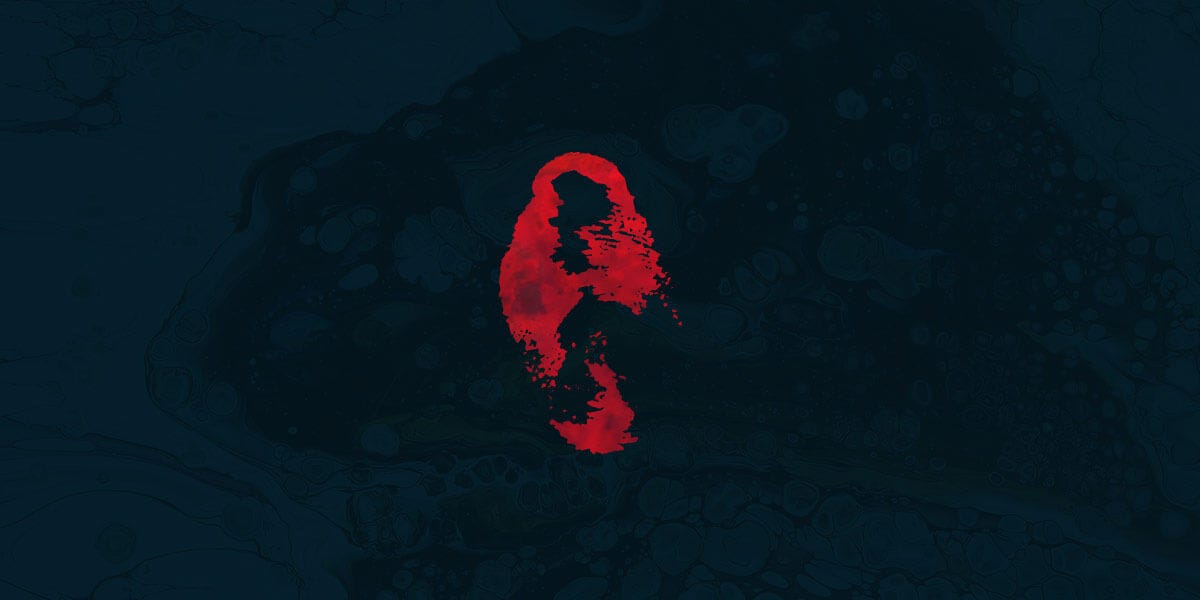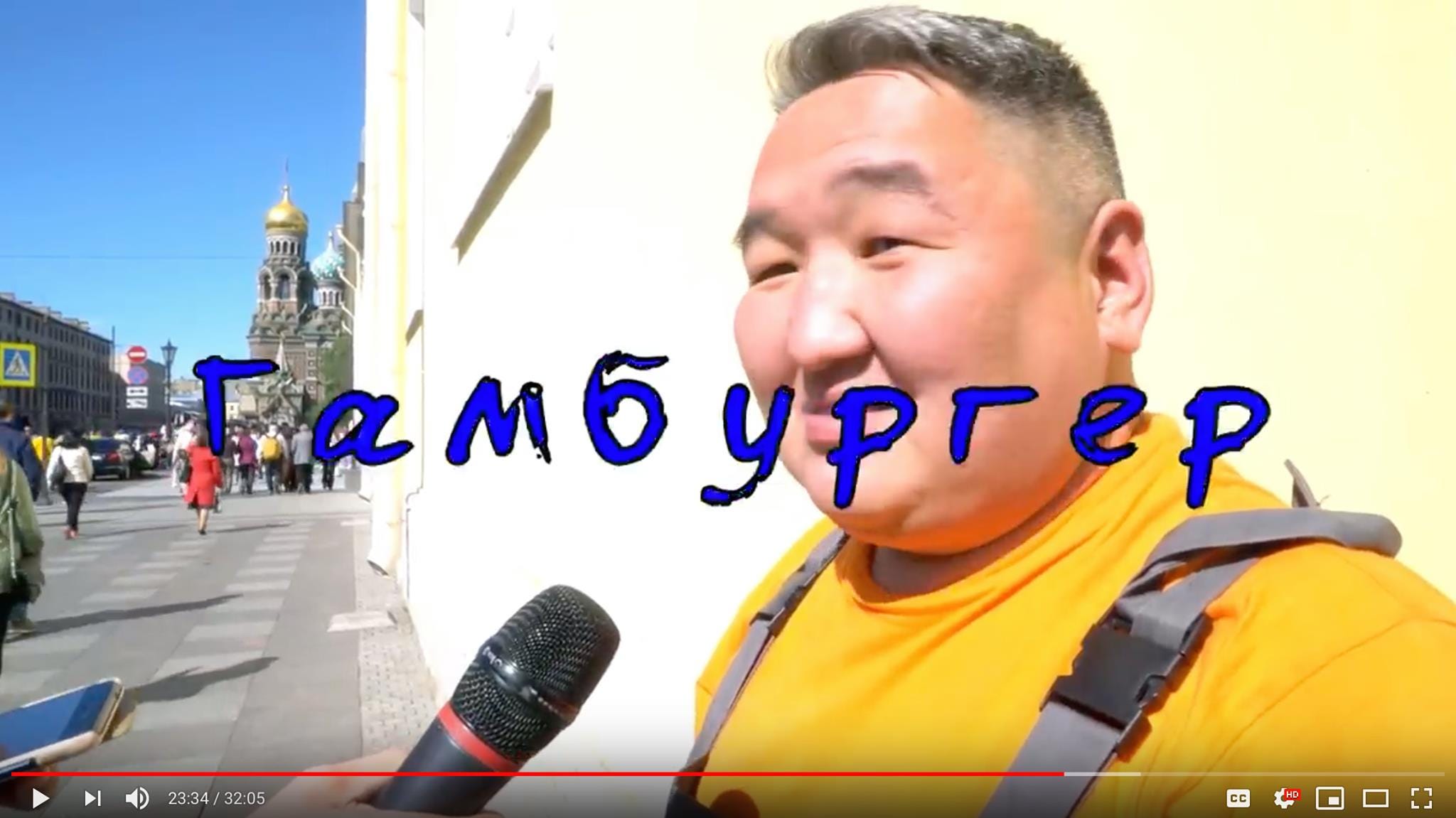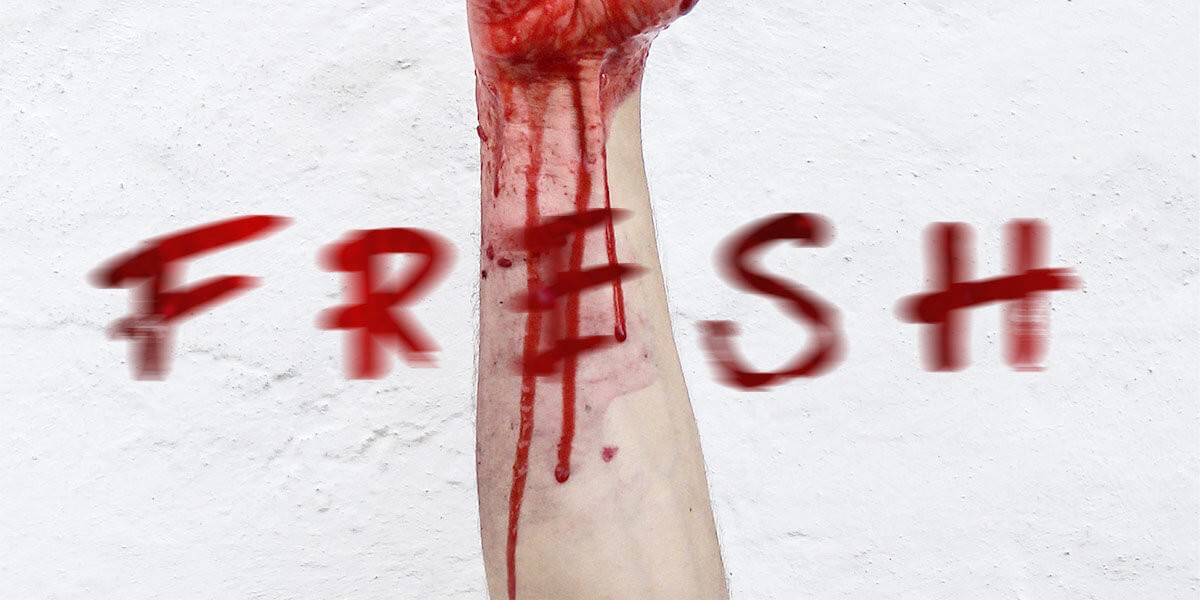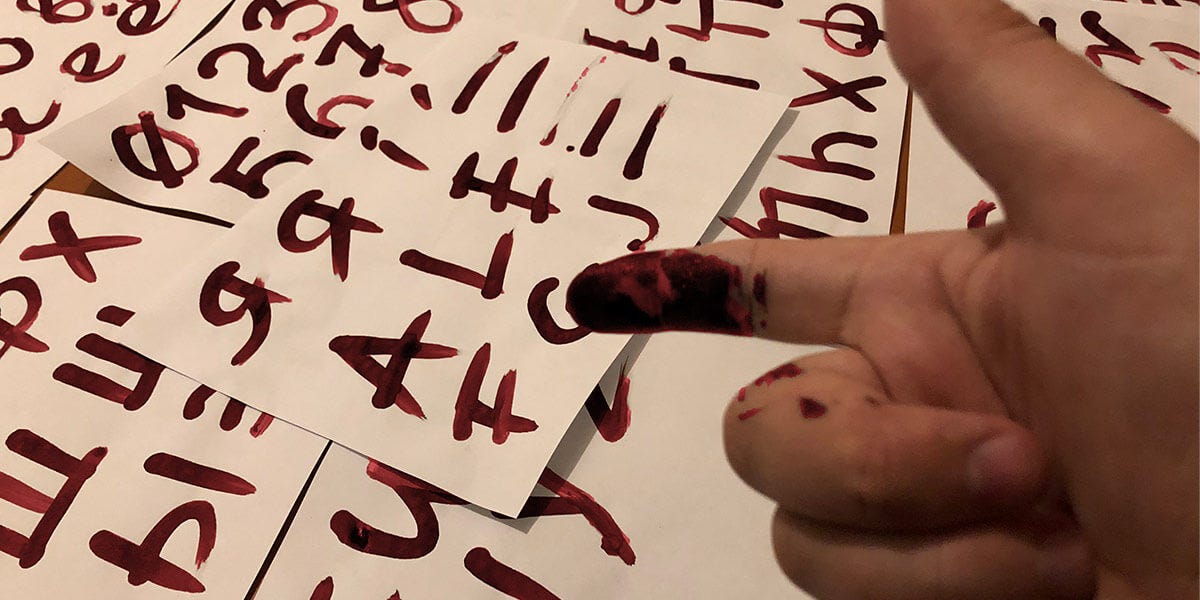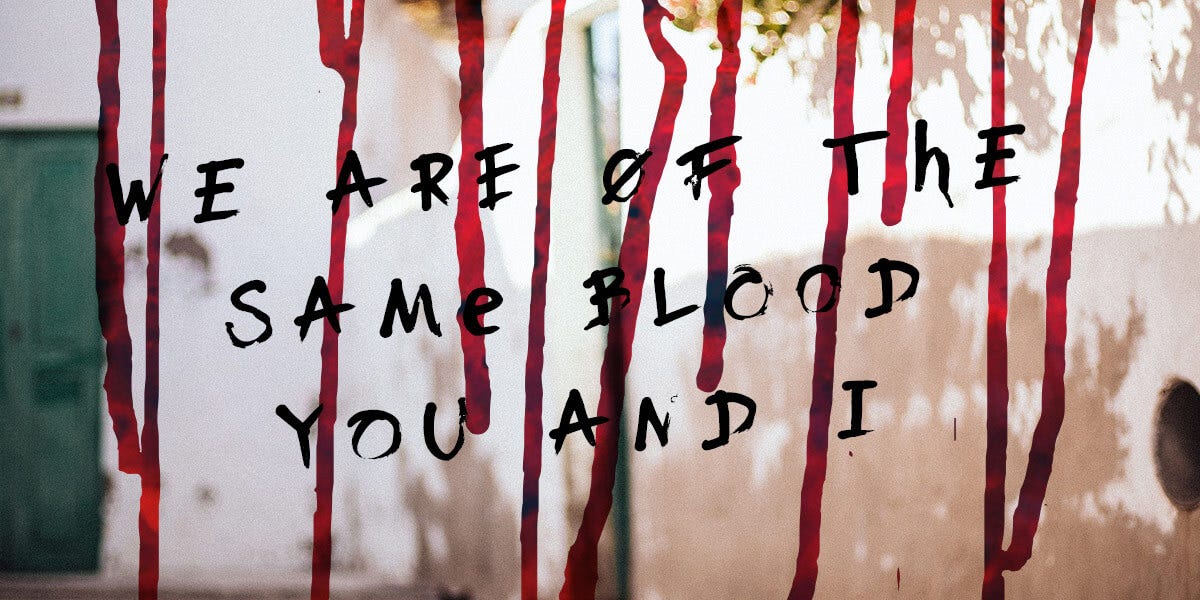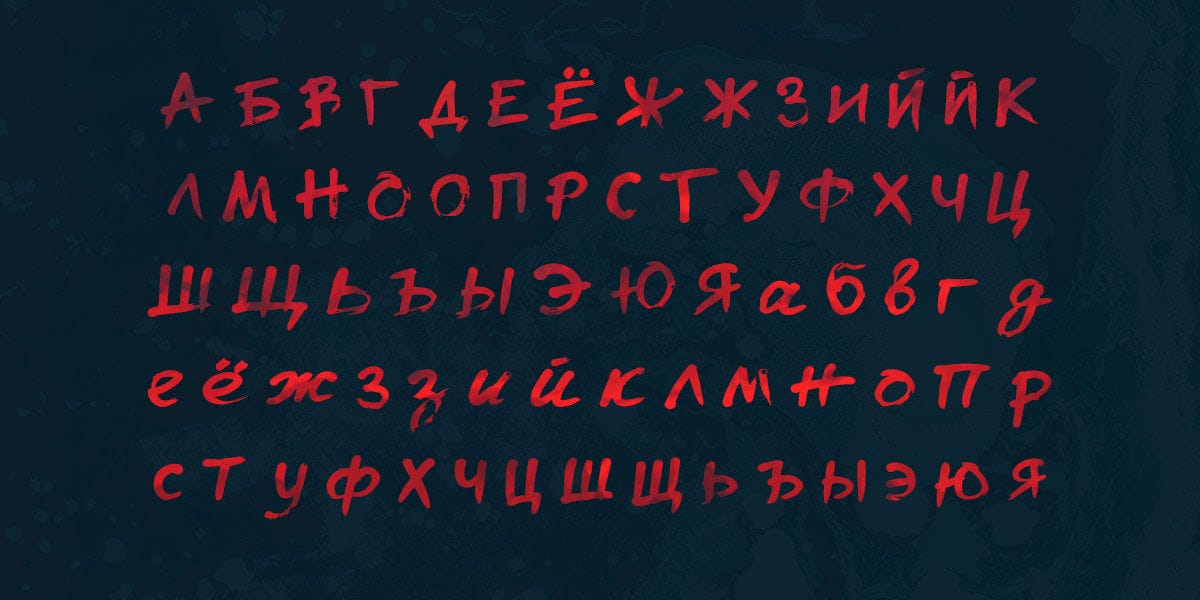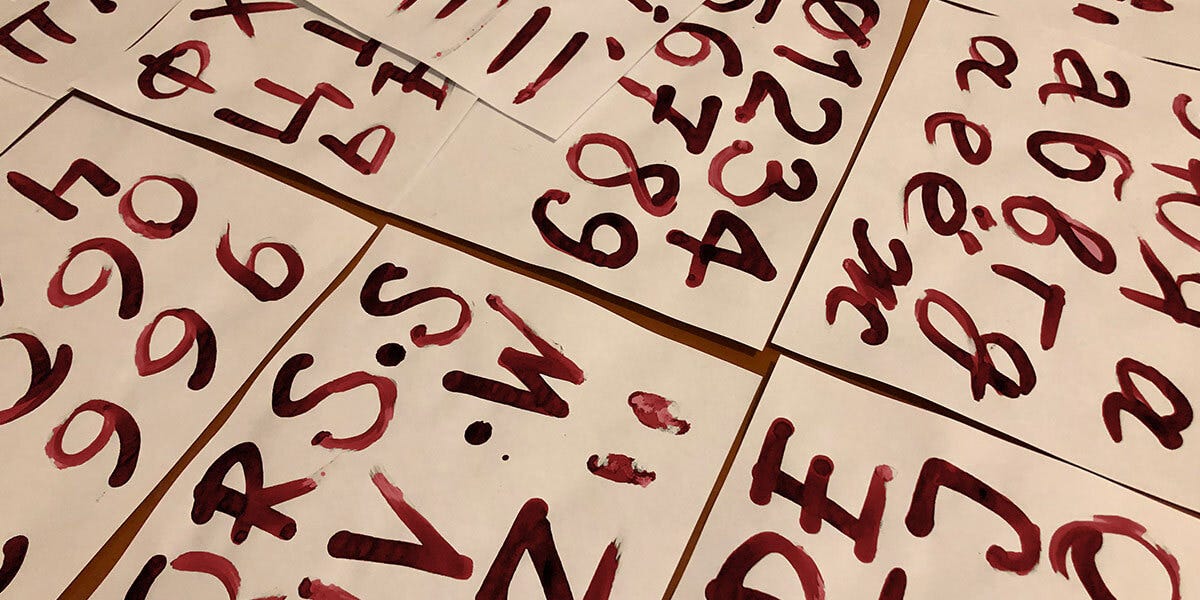
Шрифт FE Blud или кровавый перформанс 🎃
В необычной коллекции шрифтового бутика «Фонт эксорт» есть шрифт, ставший результатом не проектной деятельности, а кровавого эксперимента.
Для создания неповторимых контуров и передачи экспрессии от жизни на бумагу, художник шрифта — исключительно в рамках акта творения — рассек указательный палец правой руки и на листах формата А4 изобразил собственной кровью латино-кириллический алфавит.
По примерной оценке в результате эксперимента потеря крови составила от 90 до 125 мл. Болевой синдром был снят обезболивающими препаратами, а медицинская помощь специалистов — не понадобилась.
После того как кровь высохла, алфавит был оцифрован и трассирован в контуры акцидентногошрифта FE Blud.
Кассу приятно разнообразили цифры и декоративные брызги крови:
Любопытный типограф на месте символа «знак копирайта» найдет отпечаток того самого пальца, которым и был нарисован шрифт:
FE Blud обладает не только интересной историей появления, но и экспрессивным характером, благодаря которым превращается в мощный инструмент для передачи эмоций.
И не обязательно только острых эмоций. Юмор ему тоже по плечу:
Ну разве не прелесть?